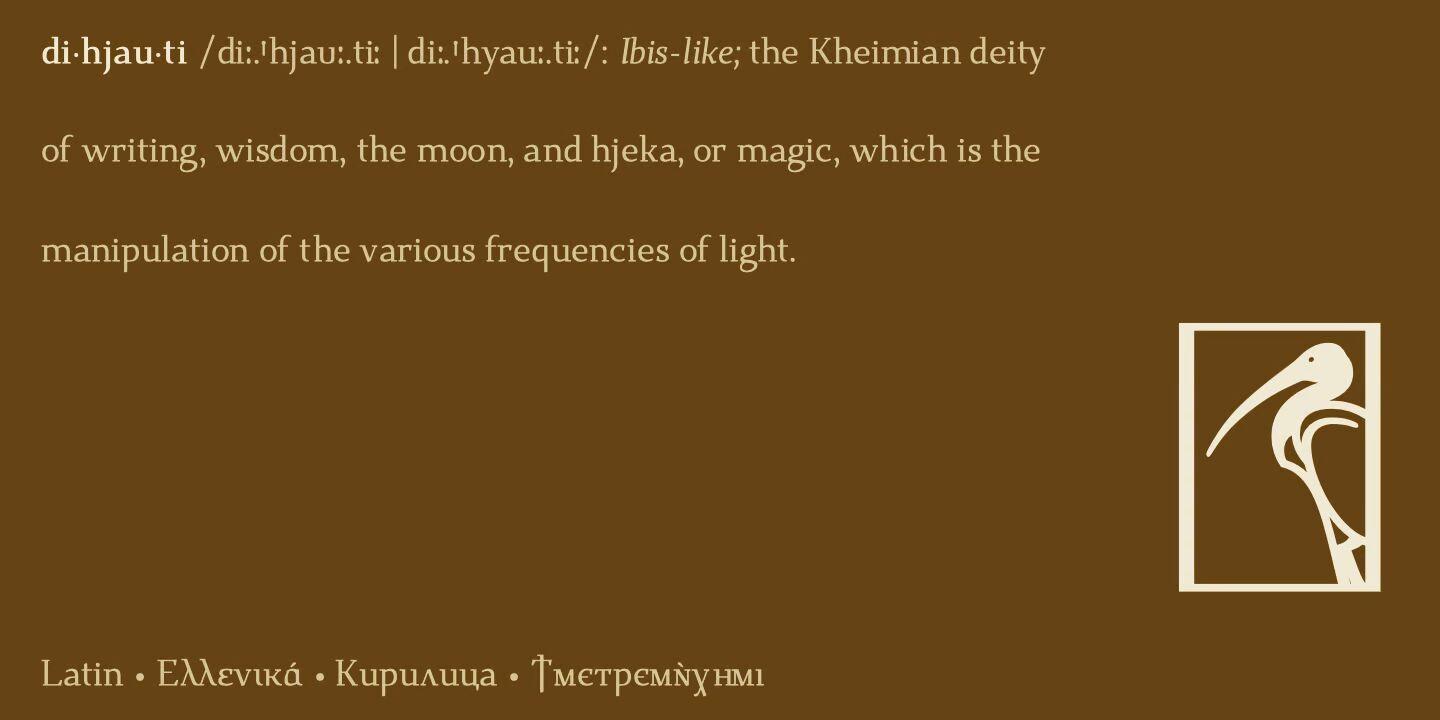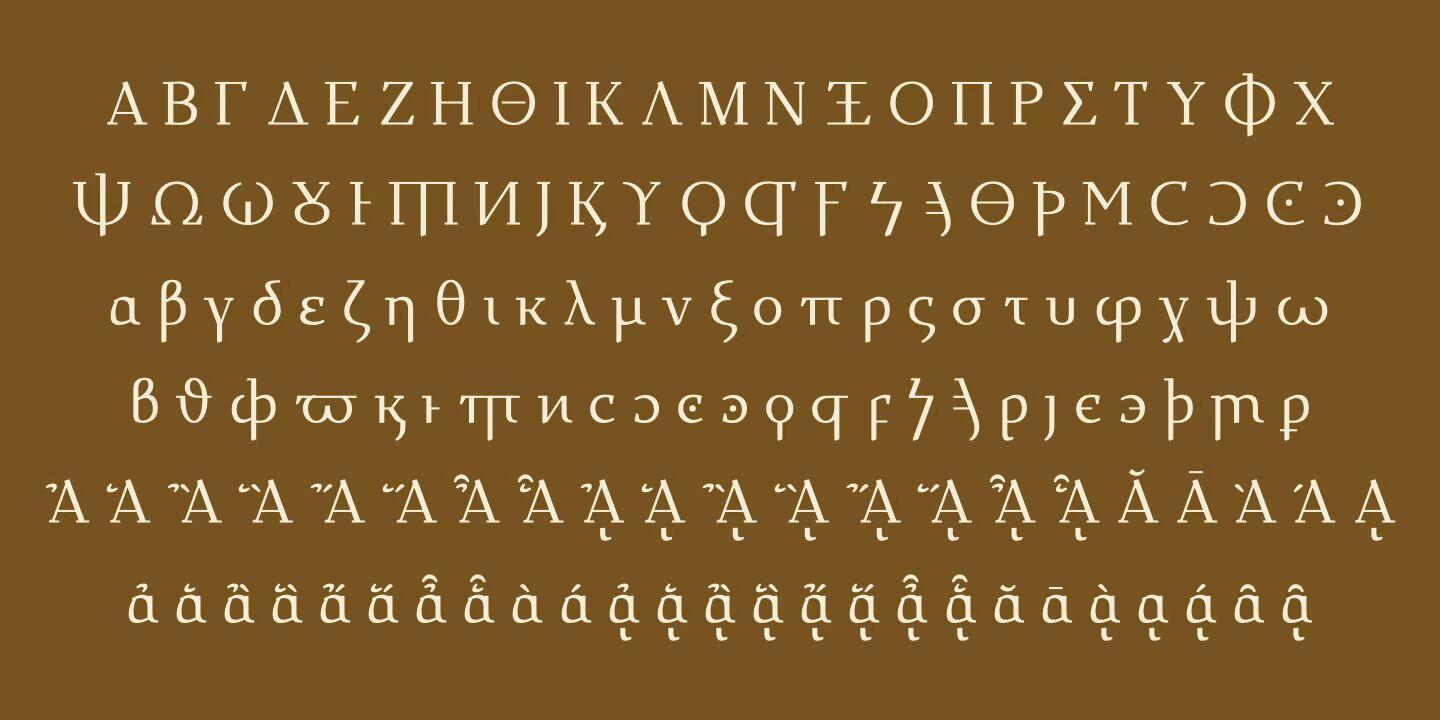
Dihjauti Font Family
Dihjauti est moderne et majestueux basé sur Electra de Dwiggin avec des nuances de Palatino et Perpetua. Comme ses inspirateurs, il présente des contreforts et un espacement larges, qui le tempèrent et lui donnent de la chaleur, le rendant confortable et bien adapté aux textes plus longs. Il est équilibré, de la ponctuation aux signes de référence et symboles. Sa conception prend en compte tous les caractères supplémentaires pour les langues que peu de polices prennent en charge, comme l’Afrique et les Premières Nations.
Ces caractères supplémentaires, tels que Edh, Esh, Gamma, Ezh, Yogh, les fricatives pharyngées, les consonnes clic, qui ont ajouté des versions majuscules, les arrêts de glotte, et cetera, semblent en réalité appartenir, au lieu d’être des réflexions après coup. L’italique incorpore une touche d’Arrighi. Il comprend tous les systèmes de transcription pertinents pour les alphabets latin, cyrillique et grec, le copte standard et les caractères supplémentaires pour les Teuthonistas et les Premières Nations. Il répertorie également les pictogrammes de style égyptien (le cas échéant), les APL, divers symboles mathématiques et flèches, ainsi que plusieurs alternatives dans le PUA.
Notes : 1) Les caractères en exposant, les lettres modificatrices et les numérateurs font tous partie du tableau des exposants. 2) Les versions en gras de la police comportent des caractères alternatifs/inversés ; J’ai fait cela parce qu’il n’y a pas de différence dans les symboles mathématiques ou de ponctuation, c’est-à-dire que les versions en gras ne sont pas en gras (sauf exceptions), ce qui donne à la police une meilleure harmonie. 3) La police utilise des ancres, ce qui signifie qu’elle ne s’alignera pas correctement pour un usage linguistique ou autre sans type ouvert. 4) Pour ceux que cela intéresse, Open ou Libre Office peut accéder à tous les glyphes en utilisant Insertion > Caractère spécial.